NASA,一个被航天事业"耽误"的设计机构!
最近(NASA)正在进行中的太空探索计划——阿尔忒弥斯计划(Artemis program),其目标是重返月球并登上火星。
是以希腊神话女神阿尔忒弥斯命名,是太阳神阿波罗的孪生姐姐,早前美国登月计划叫阿波罗计划。
还发布了以希腊神话女神阿尔忒弥斯为原型设计的「登月女性 」LOGO。
标志由月球和人脸结合,五官刻画抽象,
并且推出了一系列以新LOGO为主题的电脑、手机壁纸。
不过这个LOGO只适合在深色背景中,反白使用,想要成黑色的话,可能连造型都看不出来了。
早前还发布了「阿尔忒弥斯」登月计划LOGO。LOGO正中是大写的字母A,并屹立在蓝色的地球之上,A字象征着神话故事Artemis弓箭的箭头,同时也代表即将发射的火箭。A字右上角的灰色半圆是“新月”,代表了阿尔忒弥斯的弓。围绕A字的红色线条就像飞行轨迹一样,从地球飞往月球。
不过不要以为NASA怎么“不务正业”
其实他在平面设计也是表现突出
NASA 的经典 Logo,熟称“肉丸”
蓝底是星球,星星点点代表太空
环绕白色弧线代表太空旅行
而红色箭头其实是扭曲且反挠的超音速机翼模型
没错就是我了
早期“蠕虫版” NASA标志是由 Danne & Blackburn 设计的
同时还制作了视觉设计标准手册
1983年,NASA的制服和宇航服上都是这个蠕虫标
宇宙的气息的字体
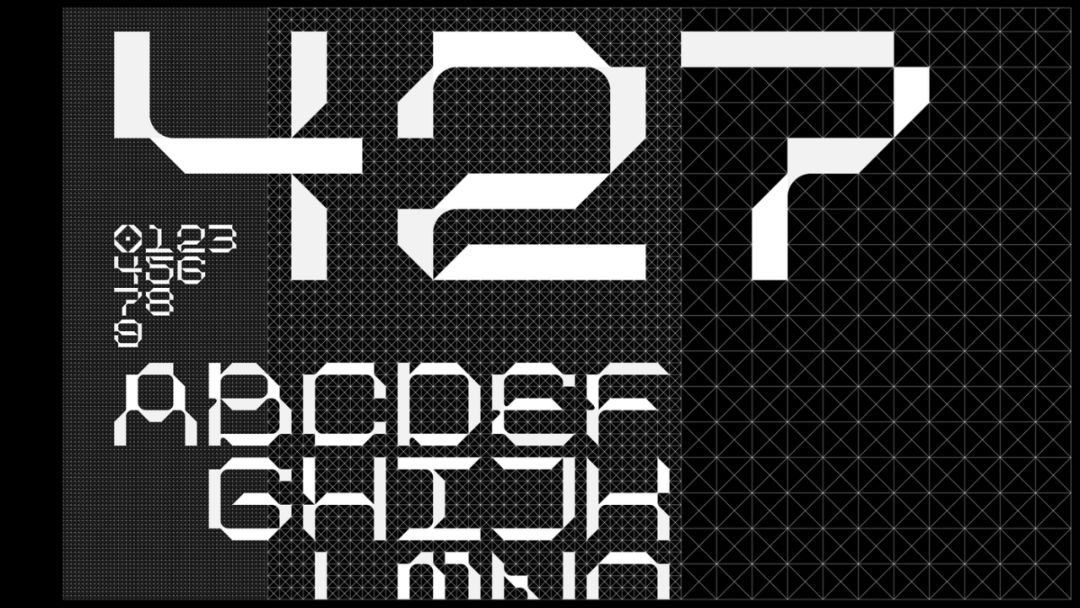
其实不止 NASA 标志非常经典
他们的每一个计划和项目
都会设计一个意义的标志
阿波罗计划的标志
阿波罗1号的标志
挑战者号航天飞机升空
执行STS-7任务的标志
哥伦比亚号航天飞机
执行STS-109任务的标志
奋进号航天飞机升空
执行STS-111任务的标志
阿波罗7号到17号的标志
还有史努比作为吉祥物的标志
而除了标志海报也是不容错过的
NASA 的下属机构 JPL(喷气推进实验室)
还设计了一些纪念海报和科学海报
周年海报
“地球是人类唯一的家园。”
纪念卡西尼号任务终结
纪念旅行者号计划
木星上风光——木星极光
纪念火星探测计划
纪念先驱者金星计划
纪念发现行星 TRAPPIST-1e
还有别具一格的招聘广告
也是非常好看
不过最为我们熟知的就是
NASA的各种跨界联名
NASA ×IKEA
IKEA与NASA合作推出了“RUMTID”太空灵感设计系列
分别为生活的四个方面:时间、空间、水和空气。
NASA × Monkey time
Monkey time和NASA联手发行了两款 Oversize T恤
简单的黑白底色上大大的
”National Aeronautics and Space Administration”字样的印花
NASA × Champion
Champion和NASA的合作款
金属色彩的羽绒外套“Metallic Puffer Jacket”
外套上绣上 NASA及太空穿梭的绣章科幻而神秘
NASA × COACH
COACH成立50年之际也和NASA推出了联名系列——2017秋冬Space限量版系列
这一系列设计是受到“美国毫无畏惧的逐梦者和探险家”的启发
现代感和复古元素的创新设计充满对太空探索的致敬
NASA × Heron Preston
Heron Preston将自己的“环卫工”风格与 NASA的科技感结合
整体的反光效果非常有未来感复古且时尚
NASA × Anicorn
香港腕表厂商 Anicorn 和 NASA 合作的限量款自动腕表
腕表结合的是太空服元素经典的蠕虫标志
NASA × LEGO
NASA与LEGO算是多年的合作
“NASA Apollo Saturn V”运载火箭积木模型
纪念升空五十周年
还用“为太空事业做出了杰出贡献的五位女科学家”为原型
设计出了“Women of NASA”系列产品
NASA × ANTA
最近国货ANTA也加入了NASA 60周年的庆祝行列
推出了SEEED“NASA 60周年纪念款
外观设计上线条感十足极具未来时尚感
NASA × Alpha Industries
Alpha Industries 经典的飞行员夹克
和复古情怀的 NASA 标志加上美国国旗非常和谐的搭配了
NASA × Vans
Vans 的 Space Voyager 系列灵感来自太空独有的特色和质感
别出心裁的可互换的贴片徽章
让每一位 Vans 爱好者都可以搭配专属于自己的鞋
NASA × Nike × Tom Sachs
Nike 联手知名解构艺术家NASA 狂热爱好者 Tom Sachs
打造了一款 Mars Yard Overshoe
灵感来源于 NASA 的火星登陆计划
模仿了宇航员的太空靴
还有Air Force 1 Low和Air Huarache
结合了NASA经典配色
还有这些星球周边
“业余”设计都做得怎么的好
NASA真的是一个被航天事业"耽误"的设计机构